История готических шрифтов | artlab.club
Заинтересовавшись историей шрифтов я постоянно нахожу что-то полезное и интересное, чем и стараюсь поделиться. Сегодня речь пойдет о готических, очень узнаваемых, шрифтах (многие именно с них начинают обучение каллиграфии).
Интересно, что готический стиль написания берет свое начало из греческого алфавита. В 300 г. до н.э. Александр Великий (Македонский) устанавливает греческий язык в качестве единого на огромной территории. Следующая Великая Империя – Римская, переняла удобную греческую письменность, но основным средством общения у римлян стал латинский язык с его прямым антиквенным шрифтом (здесь впервые появились засечки на заглавных буквах (капителях) – serifs). Латынь была заимствована у этрусков, буквы которых, в свою очередь, основывались на греческом алфавите.
В 395 г. н. э. в конце правления императора Константина, Римскую Империю наводнили германские варвары, уже имевшие к тому времени свой рунический алфавит, который называют также футарком
Вот образец рунического алфавита готских (германских) тевтонов.Благодаря распространению христианства в этот момент появляется необходимость в книгах и появляются тысячи монахов переписчиков, которые постепенно модифицировали написание шрифта и создавали новые стили.
Ниже приведен пример кельтского письма, называемого унциальным (scriptura uncialis), потому, что литеры записывались на четырёх направляющих линиях, отстоящих друг от друга на расстоянии одной унции (24,5 мм). Кельты сделали римское написание букв мягче и выразительнее
Дальнейшее развитие унциального письма привело к появлению четырёх форм: ирландское письмо (Ирландия и Англия), меровингское (Франция), вестготское (Испания) и старо-италийское (Италия). Между 900 и 1000 г.г. наиболее развитое меровингское письмо преобразовалось в каролингское
, ставшее нормой для переписывания церковных книг.
Это письмо характерно появлением маленьких (то, что мы теперь называем “строчными”) букв. К концу 1000 г. н. э. из каролингского развилось романское письмо (Romanesque), которое к 1200 г. приобрело уже почти готический вид. Он и теперь известен под именем Black Letter, или, чаще, — старо-английское письмо (Old English).Ранний готический шрифт (протоготический) – был широко распространен в западной Европе и использовался со второй половины 11 века до середины 13 века, в период между концом каролингской эпохи и началом готической. Поэтому может рассматриваться как переход от каролингского минускула к текстуре, т.к. сочетает в себе элементы этих написаний.
Тексту́ра (от лат. textura — ткань, также textura quadrata, Blackletter, Old English) — основная разновидность готического письма. Словосочетание «готический шрифт», как правило, ассоциируется именно с этим вариантом. Появилась в начале 13 века. Своё название текстура получила за то, что покрывала страницу равномерно и на определённом расстоянии страница, заполненная таким шрифтом, напоминала текстуру ткани.
Bastard Secretary – чем более формальным становился манускриптный шрифт, тем больше была необходимость в более функциональных шрифтах в дополнение к ним. Поэтому изысканные текстурные шрифты дали начало шрифтам для менее престижного, повседневного письма. Несколько взаимодополняющих написаний развивались как на региональном, так и на национальном уровне, быстро превращаясь в полноценные шрифты. И классифицировались они как «гибридные» (bastarda), термин, обозначающий шрифты смешанного скорописного и текстурного происхождения.
Швабахер, швабах (нем. Schwabacher) — разновидность готического письма, зародилась в 15 веке. Ломаное письмо с округлёнными очертаниями некоторых букв. Этот шрифт доминировал в Германии с конца 15 до середины 16 века. После чего был заменён на фрактуру, но оставался популярным до 20 века. Похож на текстуру, но более округлую, простую версию. Роту́нда (итал. rotonda — круглая) — итальянский вариант готического письма (полуготический шрифт), появившийся в XII веке. Отличается округлённостью и отсутствием надломов. Получил начало от каролингского минускула. Готическое влияние на написания восточной Европы между 10 и 13 веками получило сильнейшее сопротивление в Италии. Четкие формы классических написаний, использование каролингского минускула способствовали появлению шрифта, отличающегося от готического более круглыми, открытыми формами и короткими выносными элементами. Был распространен вплоть до 18 века, в том числе получил широкое распространение в Испании.
Ротунда явилась уже переходным шрифтом от готики к антикве. На севере Европы, особенно в Германии, шрифты “настоящей готики” постепенно переродились в более широкие и удобочитаемые литеры “поздней готики”.Безмерный вклад в то, что готический шрифт до сих пор легко узнаваем и популярен, сделал Иоганн Гутенберг (Iogann Gutenberg). Прежний процесс переписи целой книги вручную был утомителен, трудоёмок, как следствие книги стоили баснословно дорого и были редки. Изобретение же Гутенберга – печатный станок и многократное использование отдельных свинцовых буквенных литер, позволило за 10 лет наводнить всю Европу печатными лавками и книжными ярмарками.
Каждая литера проектировалась Гутенбергом отдельно и гравировалась вручную в твёрдом металле. Эта основополагающая технология горячего металлического литья получила исключительное распространение, совершила переворот в системе коммуникаций Запада и применялась вплоть до 60-х годов XX-го века.
Для первых отливок литер Гутенберг выбрал готический шрифт, как господствующую форму рукописного шрифта того времени.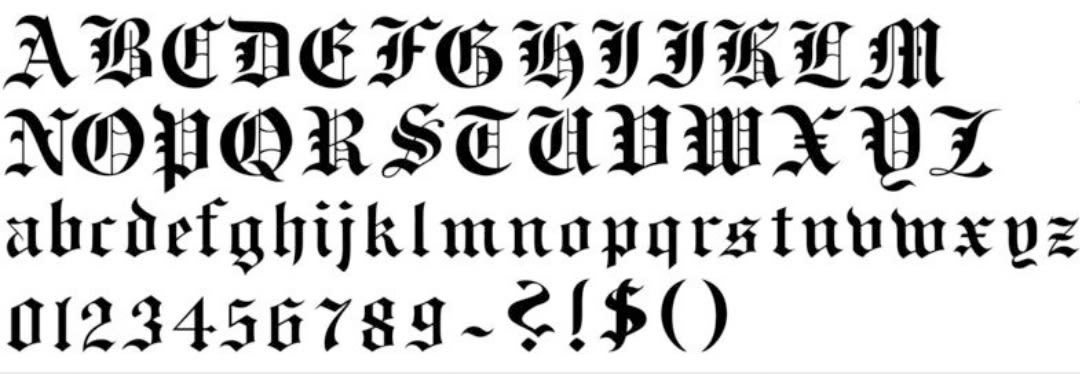
Признаться, пока я не интересовалась этим, мне казалось, что готическое письмо все одинаковое, а выяснилось, что столько разных интересных вариантов.
Если вы хотите попробовать скопировать образцы из поста, вам пригодится ручка Parallel Pen, маркеры с плоским пером или обычное плоское перо. В старину использовались специальным образом заточенные перья, но благо технологии позволяют сегодня упростить этот процесс. Если вы уже пробовали писать готические шрифты — делитесь впечатлениями и картинками.
Шрифт Warfake
Шрифт Warfake — это высококонтрастный шрифт blackletter, который добавит смелости вашим проектам и вдохновит вас на создание чего-то уникального и современного. Этот шрифт также поставляется с альтернативными символами и многоязычной поддержкой.
Шрифт Snoserose
Шрифт Snoserose — это тщательно продуманный шрифт, который имеет очень тяжелое ощущение черного металла. Snoserose подходит для логотипов металлических групп, товаров, одежды, одежды или всего, что нуждается в ощущении блэк-метала.